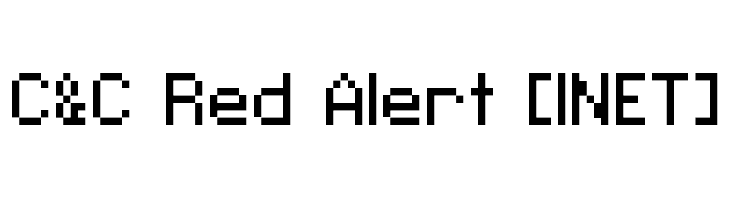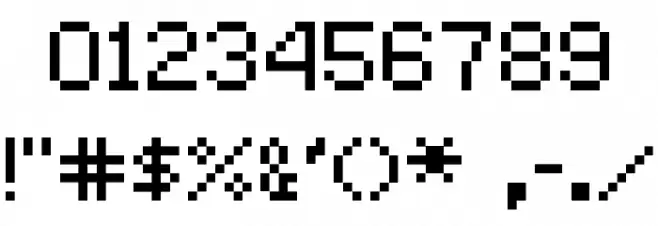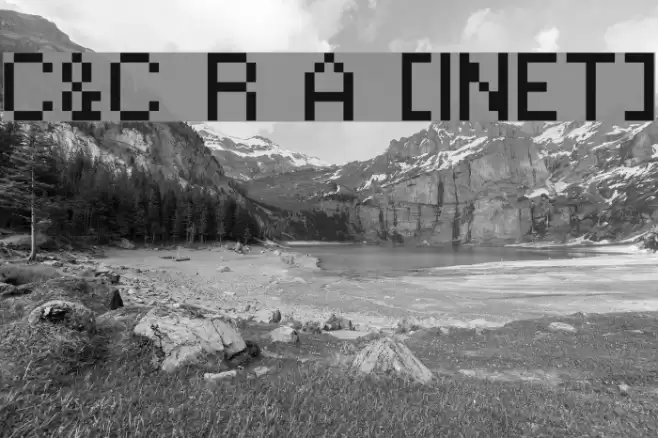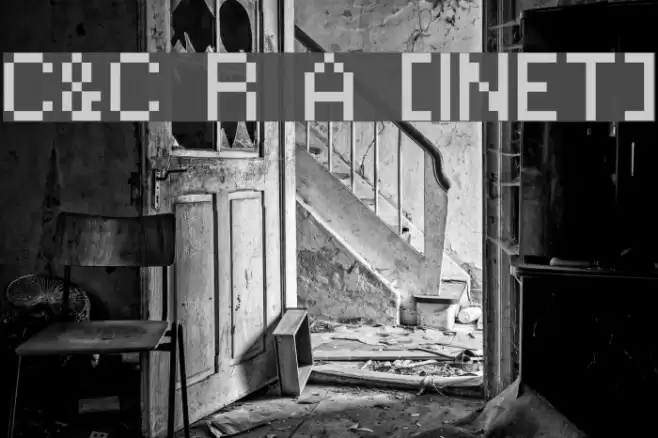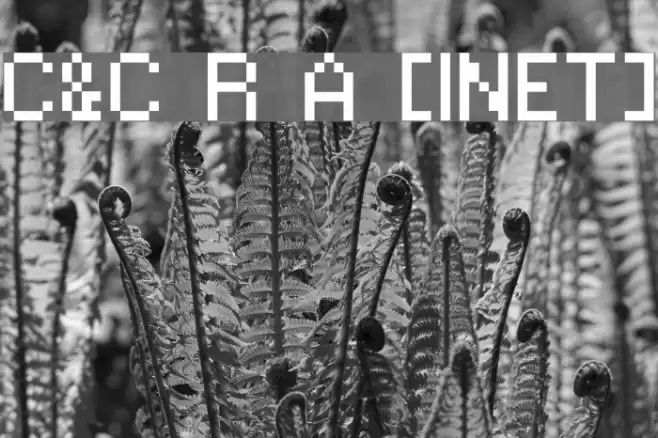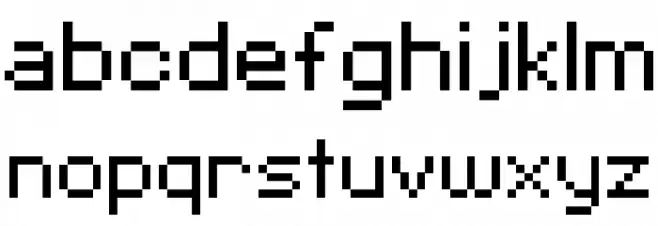
C&C Red Alert [INET] Font
| Categorie | Pixel |
| Caso d'uso | Logos, Headlines, Digital Art |
| Progetti proposti | Ideal for retro video game designs, tech-themed posters, digital art projects, and any creative work that seeks to evoke nostalgia for early computing. |